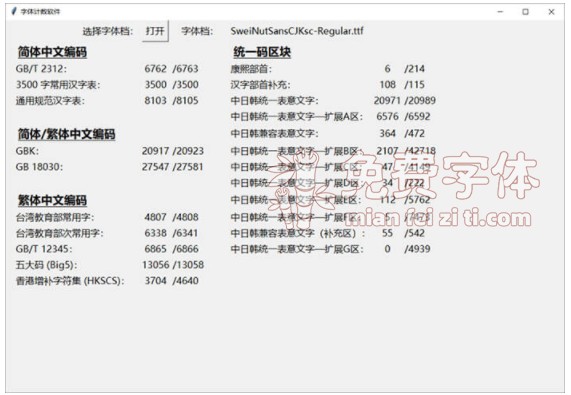
狮尾螺帽腿黑体:思源黑体增加斜角改造免费商用字体资讯
狮尾螺帽腿黑体基于思源黑体增加斜角和拔脚改造,更加简明现代化的字体。支援简体中文、繁体中文、韩文与日文;欢迎大家自由应用、自由优化、自由改作!
狮尾螺帽腿黑体的特色是,“口”字的转角处增加一个斜角,外形有点像螺帽。
狮尾螺帽腿黑体和狮尾螺帽腿黑体差别在有没有拔脚,“拔脚”就是会有较少的笔画,例如移除“口”字的左右下角会多出的短线条。有拔脚的字会较圆,但是会造成有些字因直接去掉腿后左右不平衡、左右不对称的“悬空”问题。改使用“腿”系列字体就不会有这个问题。